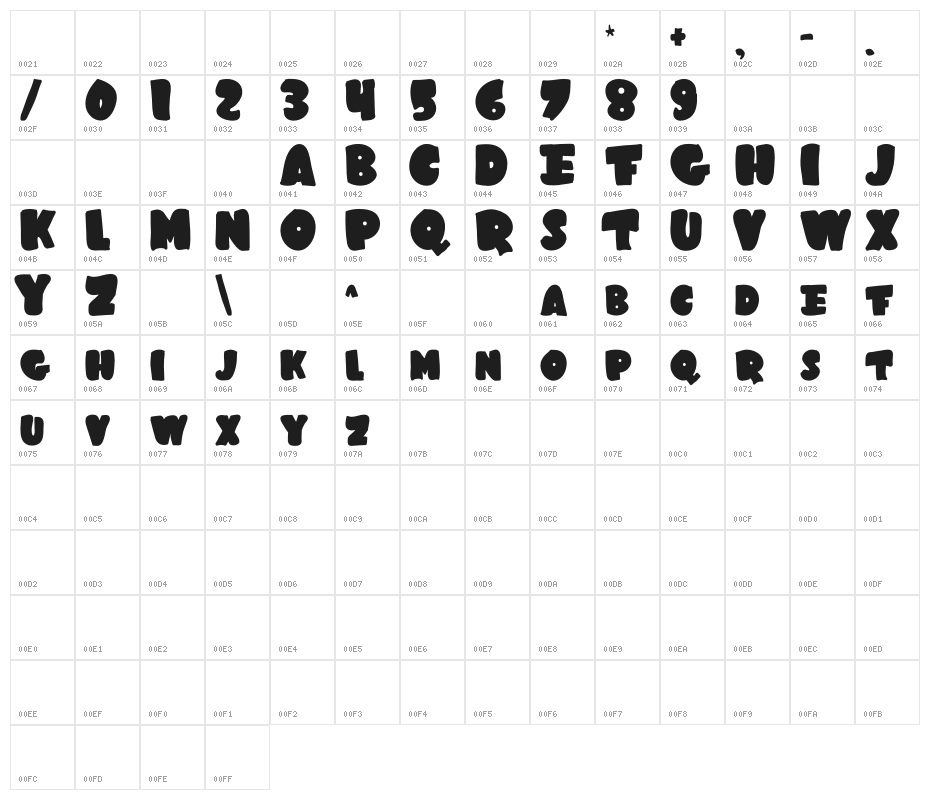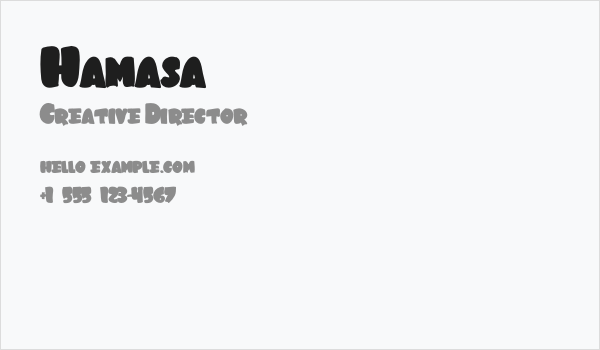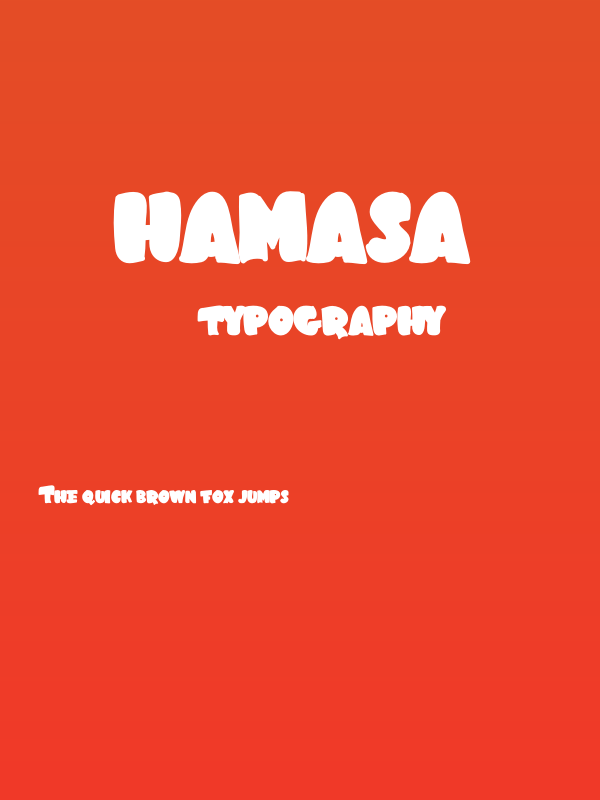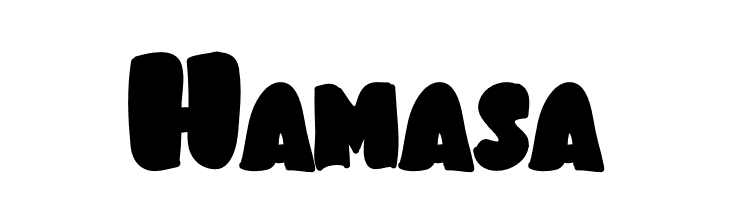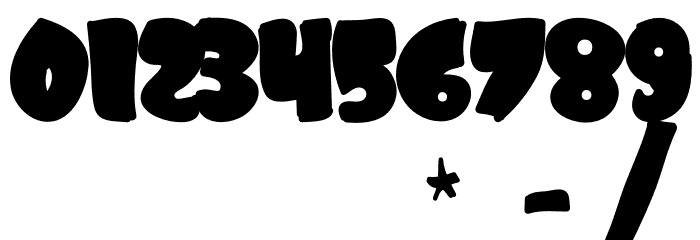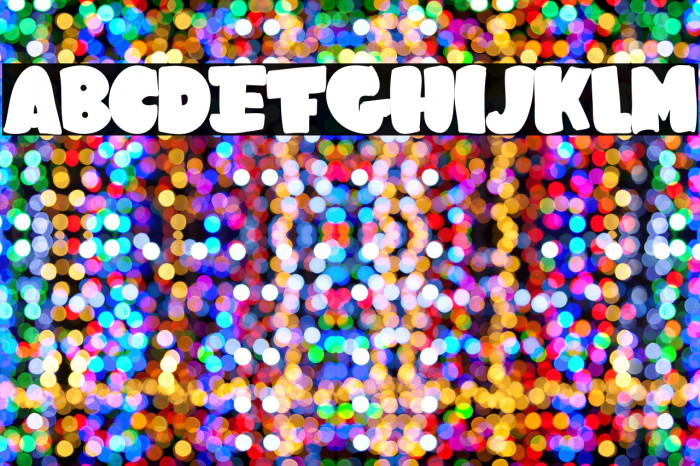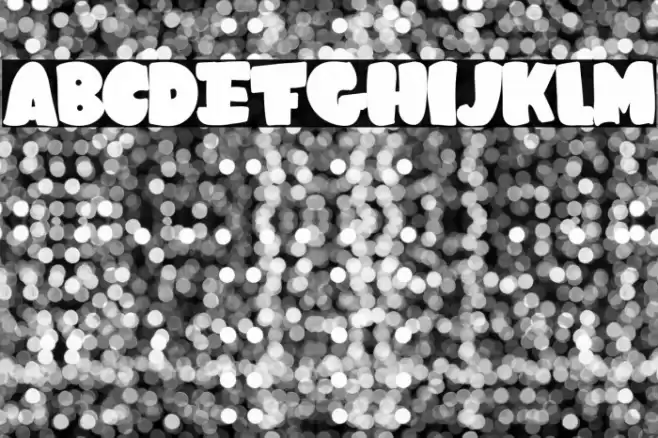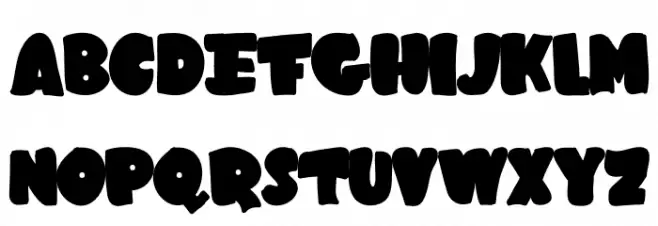
Hamasa Font
✎ Cartoon
| Style général | Playful, Cartoonish |
| Projets proposés | Ideal for children's books, comic strips, playful branding, and party invitations. |